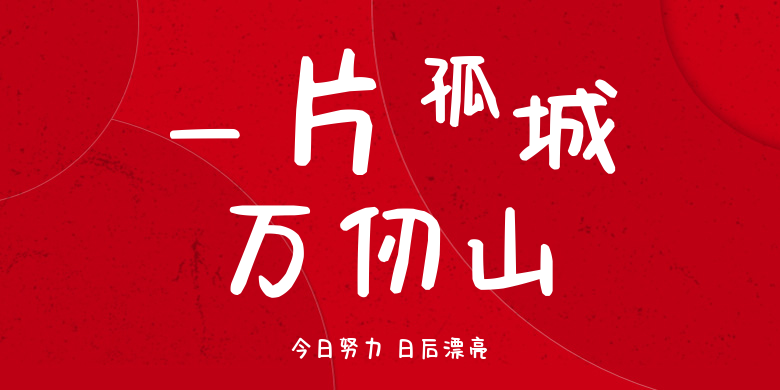
今日努力 日后漂亮
今日努力 日后漂亮,这款字体结构工整、笔画清晰,兼顾美观与易读性,适用于标题、正文、海报、包装、LOGO 等多种场景。字形优雅稳定,风格百搭耐看,适配日常排版与创意设计,让文字呈现更舒适、更具质感。今日努力 日后漂亮一笔一画,皆是细节,以均衡的比例、流畅的线条打造舒适视觉体验,字形端正大气,风格简约现代。无论是商业设计、品牌宣传还是日常排版,都能轻松驾驭,让文字更有格调与力量。今日努力 日后漂亮字体下载。